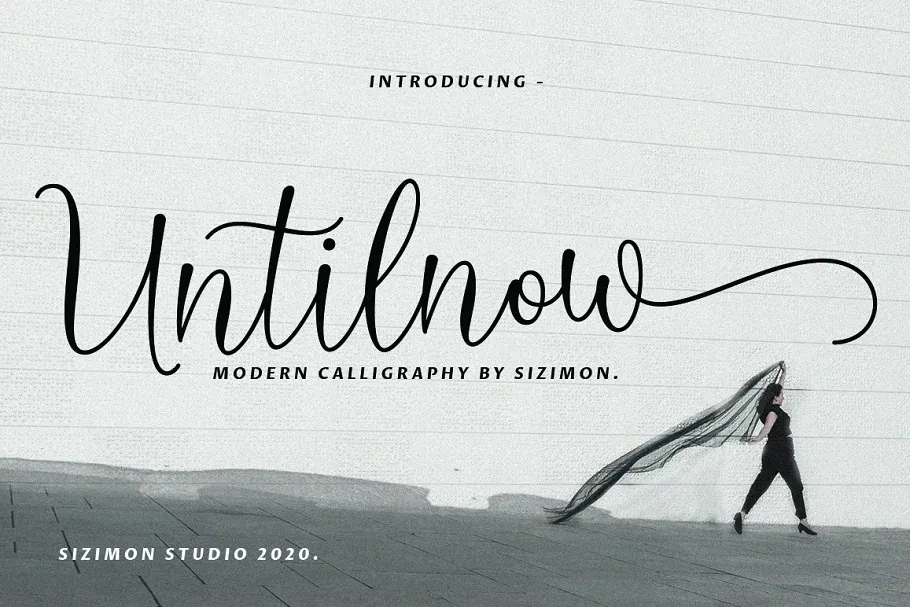
A fonte ‘Untilnow’ é uma elegante tipografia script redescrita para transmitir elegância e estilo. Com sua estrutura fina, feminina e amigável, ela se destacaria perfeitamente em qualquer aplicação que deseja aparentar elegância e modernidade. Desenvolvida especificamente para marcas de moda, lojas online, blogs de tendências ou qualquer negócio que busque uma aparência sofisticada e deslumbrante, ‘Untilnow’ é o ideal para quem procura algo mais do que apenas um design gráfico versátil. Para quem está procurando por fontes scripts, este pode ser o item perfeito na sua lista. Suas linhas finas permitem um texto fluido e elegante, enquanto seu aspecto feminino e amigável fazem dela uma ótima escolha para marcas que desejam transmitir confiança ao mesmo tempo em que mantêm-se atraentes e atemporais. Esta fonte é perfeita para criar textos de alta qualidade para sua marca, seja o nome de seu negócio ou conteúdo informativo. Afinal, uma boa fonte pode fazer toda a diferença no visual de um site ou material gráfico.